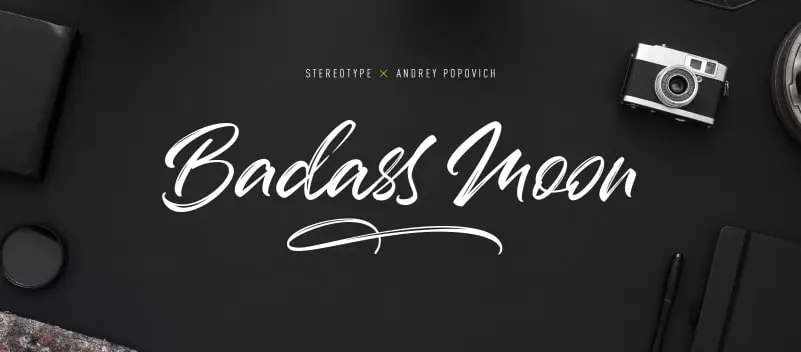
A fonte “Badass Moon Brush Font” é uma seleção única para designers aventureiros e criativos. Desenvolvida pelo Designer StereoType, Badass Moon é uma fonte script que combina os detalhes elegantes dos títulos de Andrey Popovich. Essa fonte é perfeita para aplicação em diversos ambientes gráficos, desde cartões de agradecimento e convites até editoriais de moda, logos e embalagens. Badass Moon traz um toque fresco e divertido ao trabalho, fazendo com que seja uma escolha amigável e descontraída para designers. O maior diferencial dessa fonte é sua versatilidade comercial, contando com um conjunto extenso de alternativas (115) e ligaturas contextualizadas. Com Badass Moon Brush Font você terá a capacidade de personalizar seus projetos de maneira única, mantendo a identidade e estilo da fonte. Seja para expressar seu lado rebelde em cartões de aniversário ou para incorporar uma essência fresca em sua marca, Badass Moon é definitivamente um recurso indispensável para qualquer designer que deseje destacar-se no mercado.